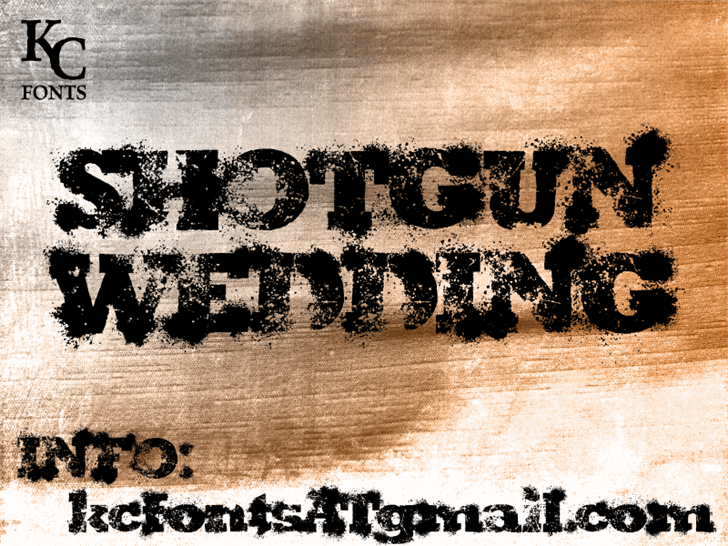
A Shotgun Wedding é uma elegante fonte serif criada pelo designer Hamilton que oferece um charme sofisticado aos projetos digitais. Este tipo de fonte possui traços arredondados e detalhes cuidadosamente elaborados, trazendo a sensação de conforto e seriedade associada às famosas fontes serif. Ideal para aquelas criações que precisam transmitir uma atmosfera formal ou um certo nível de sofisticação, esta fonte oferece um padrão sólido e elegante. Suas linhas arredondadas são perfeitas para criar textos profissionais sem perder a essência desejada. Seja em aplicativos empresariais, criações gráficas ou até mesmo websites que exijam um toque de classe, a Shotgun Wedding é uma escolha inteligente. Especialmente ideal para trabalhos pessoais, esta fonte gratuita pode ser utilizada de maneira livre. Para quem busca mais liberdade e personalização, Hamilton disponibiliza opções de licenciamento comercial para aqueles que desejam empregar essa fonte em escala maior semelhante a uma versão comercial. Sempre um passo à frente para quem procura qualidade e elegância em cada projeto digital.